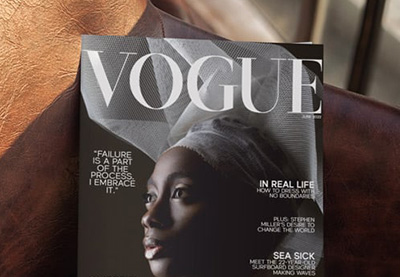
What Font Does Vogue Magazine Use?
Welchen Font benutzt das Vogue Magazin
Welche Schriftart verwendet Vogue auf ihrem Titelblatt? Entdecken Sie die Antwort in dieser umfassenden Einführung in das Vogue-Magazinlogo und die Typografie. Wir werden auch einige großartige Alternativen zu den Vogue-Schriftarten betrachten, die Sie von Envato Elements herunterladen können.
Wie lautet der Schriftartname von Vogue?
Das Logo des Vogue-Magazins wird mit einer modifizierten Version der klassischen Didot-Schriftart erstellt.
Welche Schriftart verwendet Vogue für ihren Titel? Quelle: Vogue-Website
Vogue gibt es seit 1892, und in den ersten Jahren gab es einige Designänderungen, bevor das Logo seine aktuelle Form annahm.
Vogue-Magazinabdeckung von 1892 vs. 2017. Quelle: Vogue
Welche Schriftart verwendet Vogue auf ihrem Titelblatt?
Magazinabdeckungen haben im Allgemeinen auch ergänzende Texte, die die Hauptgeschichten einführen. Neben dem berühmten Logo verwendet Vogue auch eine benutzerdefinierte Sans-Serif-Schrift namens Vogue AG, die 2004 von Terminal Design entworfen wurde. Diese Schriftart kombiniert Elemente von Futura und Avant Garde Gothic.
Welche Schriftart verwendet Vogue für ergänzenden Text? Quelle: Terminal Design
In den Innenseiten des Magazins werden Sie feststellen, dass die Typografie etwas vielfältiger ist, wobei je nach Design und Layout jedes Artikels unterschiedliche Schriftarten für Überschriften und Fließtext verwendet werden.
Vogue Magazin Schriftartalternativen
Wenn Sie vom Vogue-Logo inspiriert sind und stilvolle Magazinmastköpfe erstellen möchten, finden Sie hier einige fabelhafte Alternativen zur Vogue-Magazinschriftart.
1. Kuta Exclusive Serif (TTF, OTF)
Fängt diese Schriftart nicht die Eleganz und den Stil der Vogue-Magazinschriftart ein? Sie hat die gleichen schlanken, eleganten Linien mit den subtilen Variationen in der Linienstärke. Sie fügt bestimmten Buchstaben auch zusätzlichen Stil hinzu, wie Sie am auffälligen „K“ in diesem Beispiel sehen können.
2. Rosemode Timeless Roman Serif (TTF, OTF, WOFF)
Rosemode ist eine luxuriöse römische Schriftart, die perfekt für Magazin-Cover und ähnliche Designprojekte geeignet ist. Es ist keine exakte Übereinstimmung, aber es lohnt sich, sie in diese Liste aufzunehmen, da sie die gleichen Gefühle von Opulenz, Luxus und Stil hervorruft.
3. Elegante Serif-Schriftart (OTF)
Wenn Sie nach einer verspielten Alternative zur Vogue-Logoschriftart suchen, versuchen Sie Romanie. Es ist eine elegante Serifenschriftart, die Klein- und Großbuchstaben, Zahlen und Interpunktion enthält.
4. Alkalis Moderne Elegante Serifenschriftart (TTF, OTF)
Irgendwie schafft es Alkalis, sowohl zeitgenössisch als auch zeitlos auszusehen. Das ist perfekt für ein Magazincover oder ein Logo, also probieren Sie es für Ihr nächstes Magazindesignprojekt aus. Als Bonus können Sie es auch für Fließtext verwenden, wenn Sie möchten.
5. Luxus-Elegante Schriftart (TTF, OTF, WOFF)
Der Name sagt alles. Luxus ist perfekt für Vogue-ähnliche Magazinprojekte oder Luxus-Markenbildung. Es enthält Ligaturen und Alternativen, um Ihnen zu helfen, einzigartigen Text zu erstellen.
6. Constantine Display Serif (TTF, OTF, WOFF)
Konstantin ist etwas komprimierter als die Vogue-Schriftart, aber es hat die gleiche Eleganz und den gleichen Kontrast in der Linienstärke. Mit regulären und dünnen Versionen zur Auswahl sowie 14 sorgfältig gestalteten Ligaturen können Sie experimentieren, um schönen Text zu erstellen.
7. Vicenza Elegante Serif (TTF, OTF, WOFF)
Wenn Sie etwas mehr Ecken suchen, versuchen Sie es mit Vicenza. Es teilt einige Merkmale des Vogue-Schriftartnamens und fügt eine eigene Note hinzu. Es enthält auch Glyphen und internationale Akzente, so dass es ideal für Magazine in verschiedenen Sprachen geeignet wäre.
8. Mosce Elegante Serif-Schriftart (OTF, TTF)
Es wird nicht viel eleganter als Mosce, eine elegante Serifenschriftart, die die perfekte Mischung aus zeitgenössischem Stil und Nostalgie bietet. Nutzen Sie die OpenType-Funktionen dieser Schriftart und erkunden Sie die Ligaturen und internationalen Akzente.